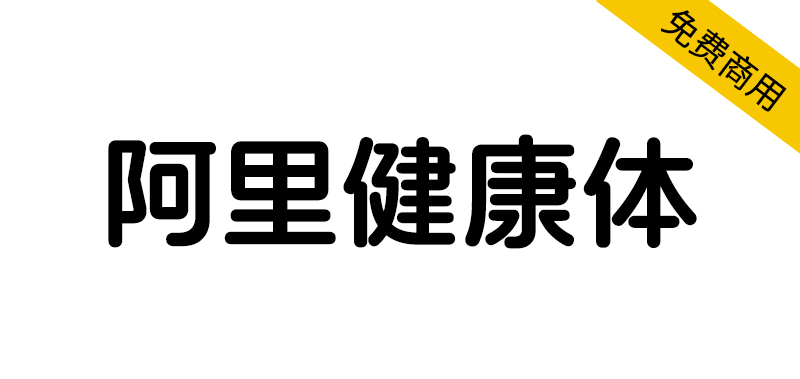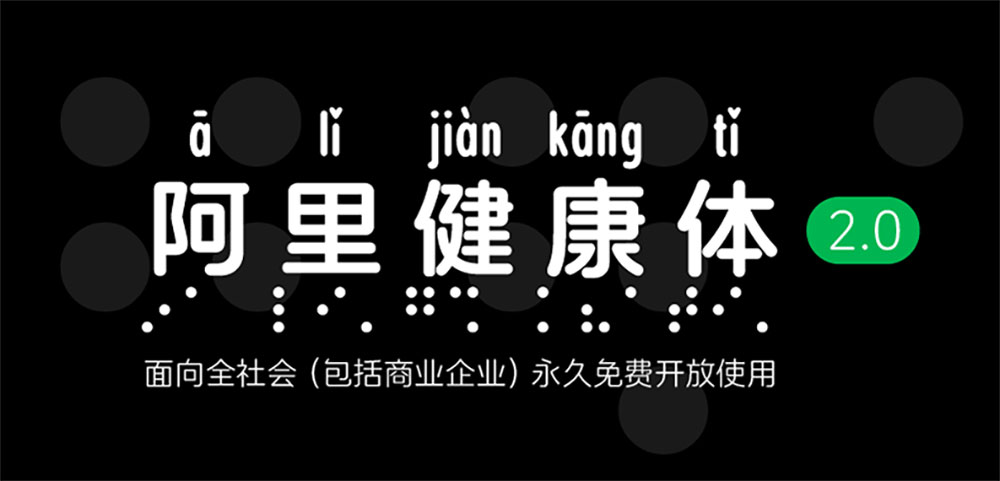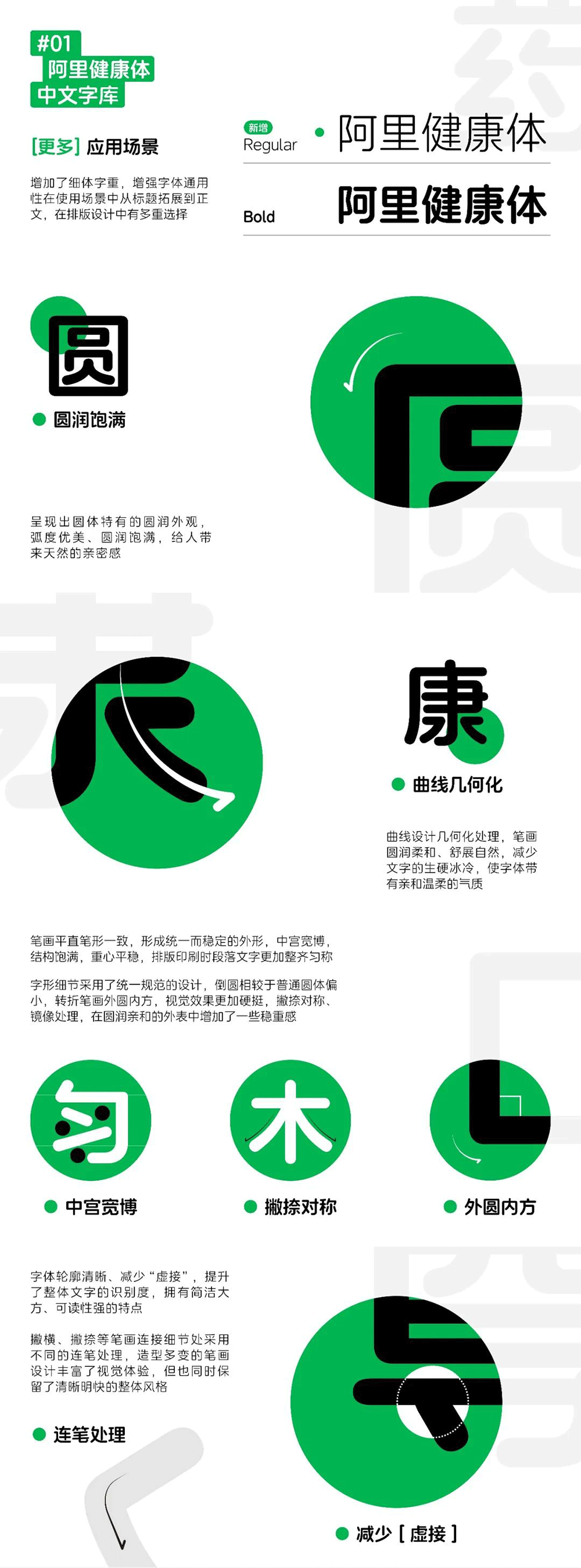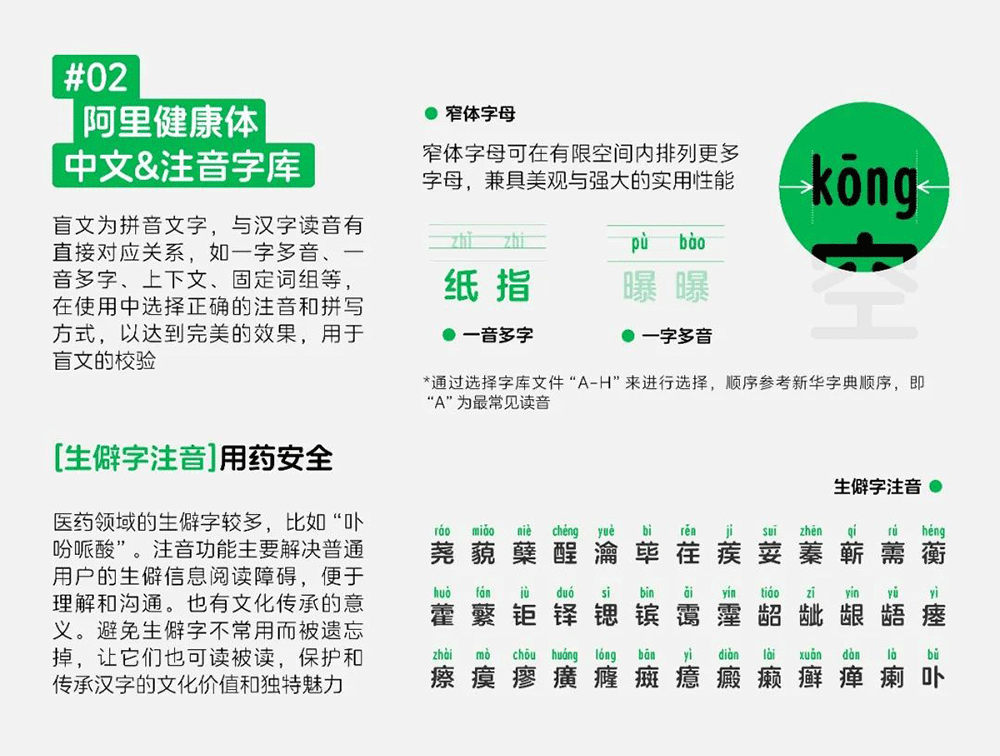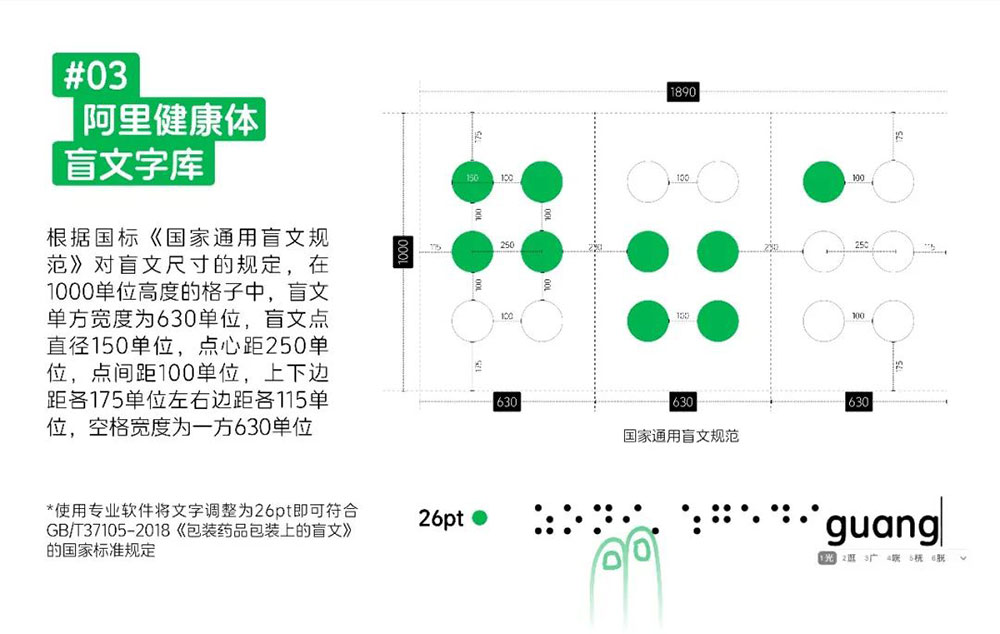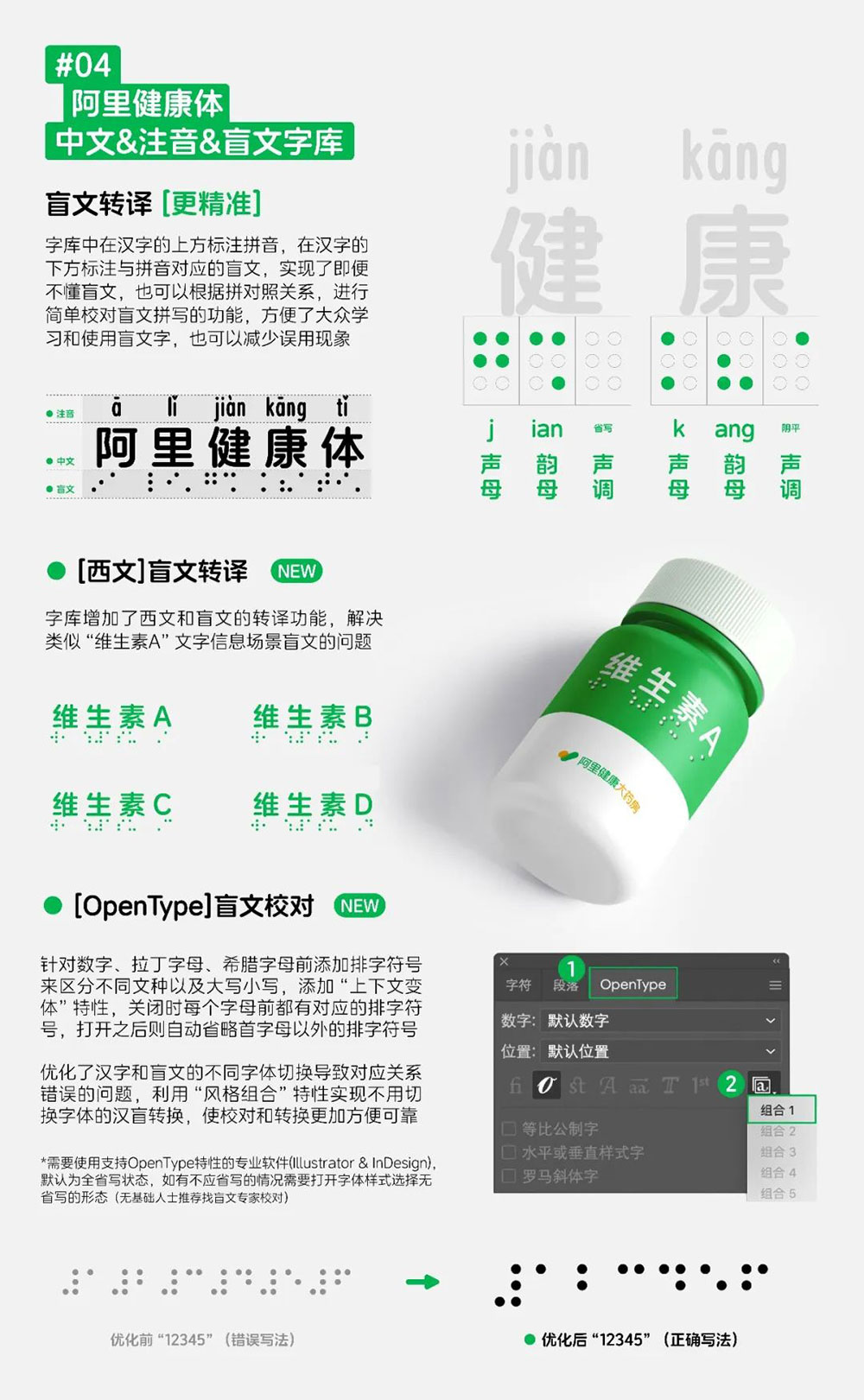
2023年11月,由阿里健康设计与方正字库共同设计开发的阿里健康体2.0家族字体正式发布。该字体以无障碍设计为初衷,以服务于视障人士为目标,是首款中文盲文注音定制字体。为了鼓励更多人关注无障碍设计,进一步推进医疗健康服务的普惠可及,阿里健康体2.0面向全社会(包括商业企业)永久免费开放使用,希望通过技术公益,推动无障碍环境建设,传递现代设计的人文关怀。
基于阿里健康有温度的关怀感的品牌定位,以及为了保持更好的文化承接性,在原始标志字体圆体风格的基础上,设计师统一了笔画特征,使字体更加规范和谐。笔画多以几何化处理方式,让字形看上去更加严谨端庄,符合阿里健康医疗行业的品牌属性。阿里健康体广泛应用于品牌文化展示、广告宣传以及物料印刷等整套视觉系统中。
此款字体是国内首款服务于视障人士的中文盲文注音定制字体,解决药品及产品包装上盲文、生僻字使用问题,为视障人士搭建一座沟通世界的桥梁。笔画多以几何化处理方式,让字形看上去更加亲和有温度。
针对药品名生僻字认读障碍问题,以及关注弱势群体用药问题,本次阿里健康体添加了注音字库和盲文注音字库,以方便药品生产各个环节参考应用,同时呼吁社会关注弱势群体,为他们送去关怀与温暖。